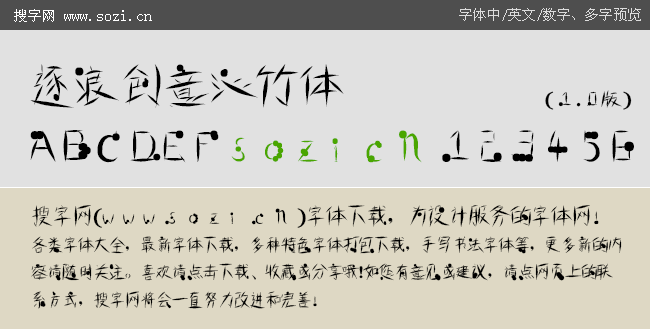
逐浪創(chuàng)意沁竹體
搜字網(wǎng)提供一款逐浪創(chuàng)意沁竹體中文藝術(shù)字體下載,逐浪創(chuàng)意沁竹體整個(gè)字形采用竹枝般的線(xiàn)條,從而具備脫俗清真的效果,特殊筆位會(huì)采用云朵裝飾,從而構(gòu)成完整的視覺(jué)傳播體系,適合應(yīng)用于廣告設(shè)計(jì)、名片設(shè)計(jì)、包裝印刷、產(chǎn)品設(shè)計(jì)等應(yīng)用。